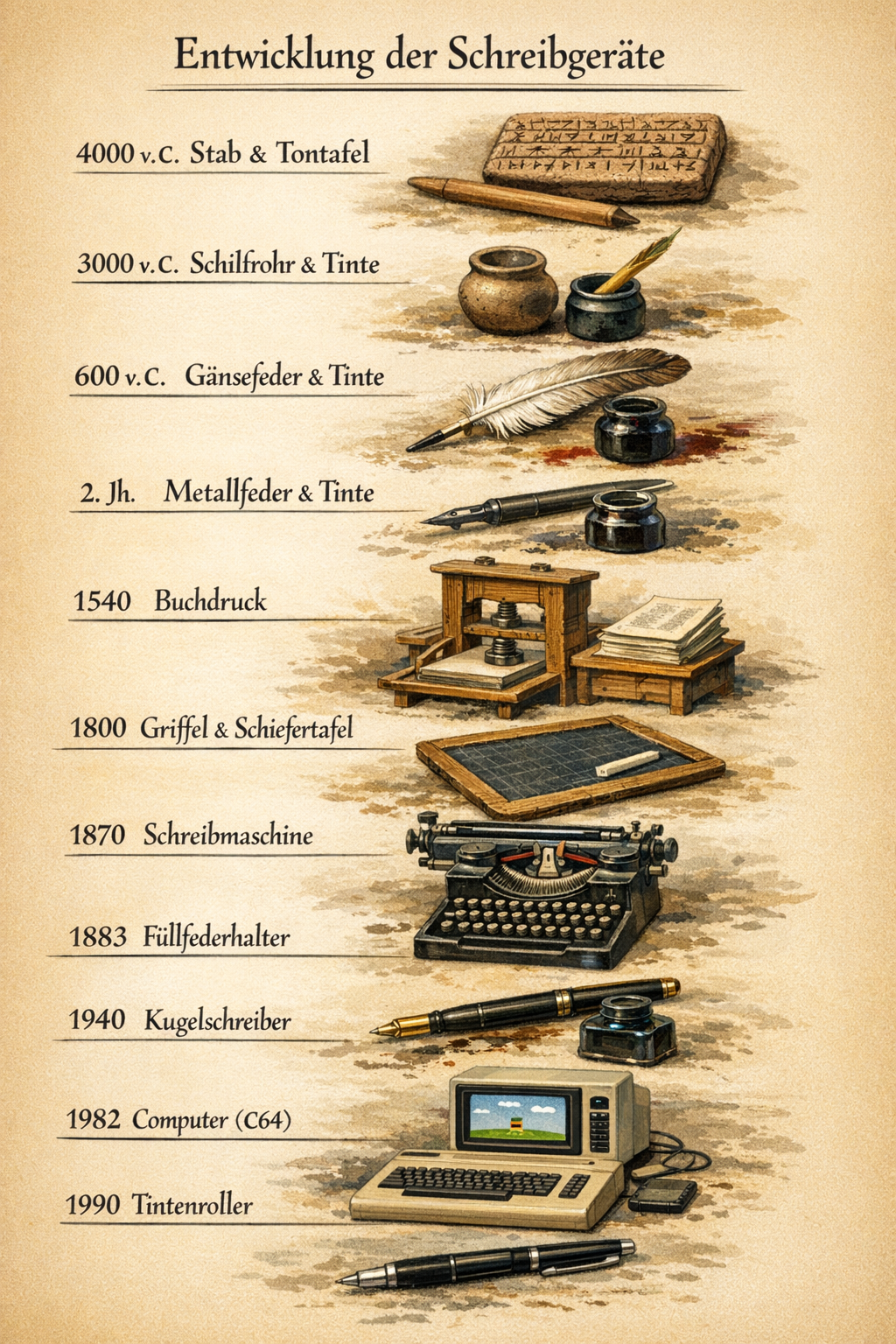
Was man zum Schreiben in der Hand hält, bestimmt fast immer auch, wie die Schrift am Ende aussieht. Eine harte Stahlfeder zieht andere Linien als ein weicher Pinsel; ein Kugelschreiber gleitet anders über das Papier als ein Bleistift. Die folgende Übersicht zeigt die wichtigsten Schreibgeräte und ihre Geschichte.
Schreibgeräte
Vom geschnittenen Schilfrohr und der Vogelfeder über Gänsekiel, Stahlfeder und Bleistift bis hin zu Füllhalter, Kugelschreiber und Tastatur — jedes Werkzeug hat die Schrift, die wir schreiben, mitgeprägt.
Werkzeuge der Schrift
Vom Schilfrohr zum Kugelschreiber